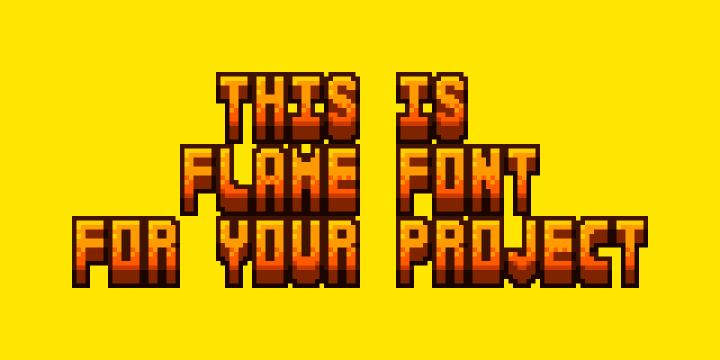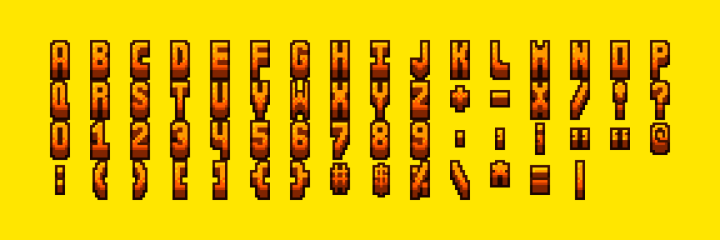
免费的像素火焰方块字体素材,使用这些自定义字体,让您的项目脱颖而出!
- 主题:火焰
- 图像:像素艺术
支持的字母和符号 —
ABCDEFGHIJKLMNOPRSTUV WXYZ 0 1 2 3 4 5 6 7 8 9 + – X / ! ? . , ; ” ” @ : ( ) [ ] { } # $ % \ * = |